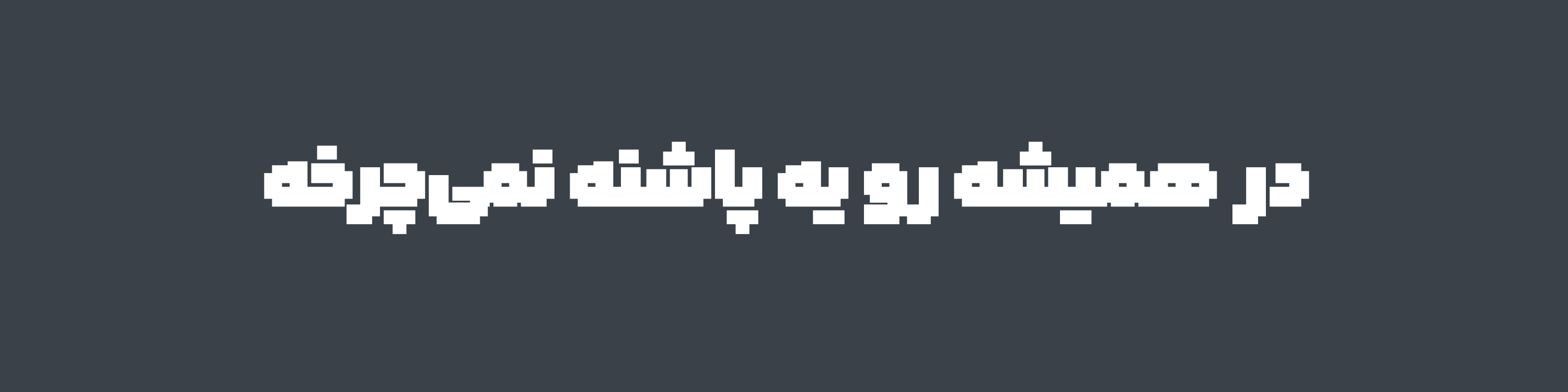
گرافیست، طراح و توسعهدهنده فونت است. متولد ۱۳۸۵ و از سال ۱۴۰۱ به طراحی تایپ فارسی مشغول است. در نوجوانی، تمرکز او بر طراحی گرافیک بود و به مرور با ورود جدیتر به حوزه تایپفیس، حرفهٔ اصلی خود را انتخاب کرد. او طراح فونتهای هاوش، رویین، سورنا و آریو است که نشاندهنده نگاه او به سادگی در جزئیات، خوانایی و نیازهای مدرن تایپوگرافی فارسی هستند.